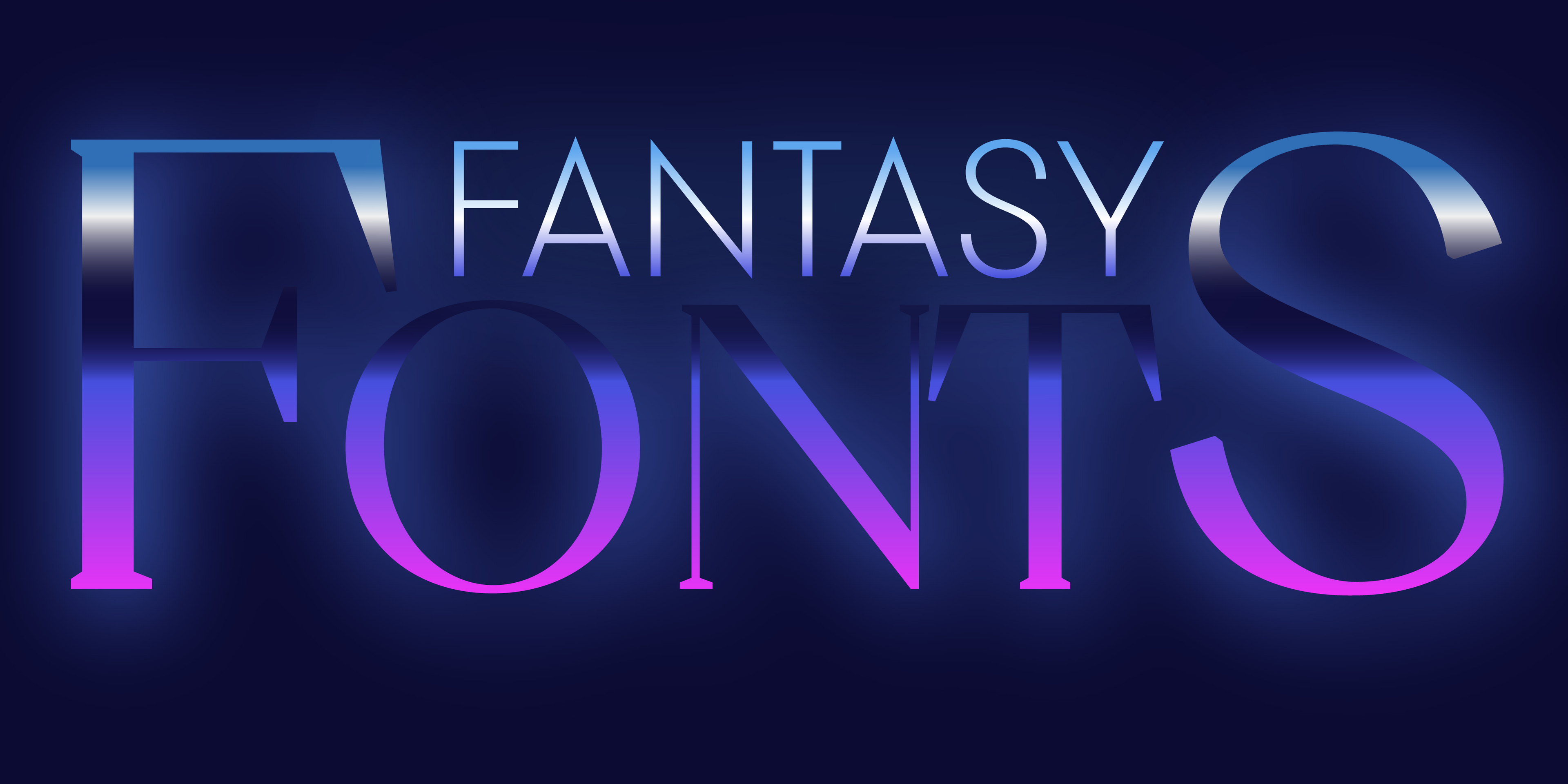
Fuentes de fantasía con un toque natural.
Veamos la primera fuente de fantasía. Se llama Kijs y viene en muchos grosores. Aquí, estamos viendo Kijs Thin . Este grosor de fuente en particular es muy ligero y, si se escribe en mayúsculas, le da a cualquier texto una sensación mágica y de fantasía. La razón es que solo algunas de las letras, por ejemplo, G, I y R, son curvas y están ligeramente inclinadas hacia la izquierda, lo que agrega un concepto más orgánico.
Como puede ver en el ejemplo anterior, gran parte del estilo de fantasía se refleja en la paleta de colores y los efectos de diseño gráfico. Un bosque oscuro, un verde natural combinado con una viñeta negra y texto en color dorado le dan a este diseño de fantasía un aspecto moderno y elegante.
En el siguiente ejemplo, observamos la misma tipografía, pero en un grosor de fuente negro. “Black” es el grosor de fuente más audaz de todos los posibles. La tipografía sigue siendo femenina y natural, pero con esta audacia intensa, se siente más orgánica. Una tipografía más audaz como esta combina muy bien con paletas de colores de fantasía de tonos púrpura y rojo.
Fuentes de fantasía nítidas y puntiagudas
La siguiente tipografía que vamos a analizar se llama Acme Light . A primera vista, parece una tipografía sans serif geométrica moderna, pero cuando la configuras con un grosor de fuente más fino y en mayúsculas, el texto se convierte en una expresión de fantasía. Por ejemplo, observa el número tres o la letra S: los trazos de la letra comienzan y terminan en un estilo cortado, similar al metal. Si agregas un subrayado, una línea superior y un degradado de color en tonos rojos, obtendrás una imagen de fantasía moderna.
Apex es una fuente puntiaguda , lo que significa que las letras con punta, como A, V, W y M, se extienden más allá de la línea de altura de la mayúscula de la línea base y forman una punta afilada. Este estilo de fuente es excelente para diseños de fantasía porque comunica espadas y ciencia ficción de manera natural.
Usa Roma Regular cuando busques una tipografía humanista de contraste medio . Es lujosa y elegante y, con un efecto de brillo dorado, se convertirá rápidamente en un texto elegante y fantástico.
Fuentes serif de fantasía
El siguiente ejemplo es la fuente Quil ExtraLight . Es una tipografía serif con serifas cortas y terminales modernas simplificadas de punta ancha. El texto en esta fuente se ve fuerte y nítido y funciona bien para títulos de portadas de libros más largos cuando se escribe en letras mayúsculas con un espaciado estrecho entre letras. Quil es similar a la fuente Final Fantasy y tiene un toque medieval.
Utilizando la misma fuente que en el ejemplo anterior, esta serifa moderna también se puede utilizar en un grosor de fuente negrita para agregar más fuerza y potencia al texto. De esta manera, algunas de las características de la fuente, por ejemplo, los extremos en forma de pico afilado, resaltan más.
Bauhaus Rose Black está disponible en varios grosores de fuente, desde Thin hasta Black. Las serifas alargadas y los diferentes grosores de los trazos de las letras hacen que esta sea una tipografía serif de alto contraste ideal para usar como logotipos de fantasía y textos de titulares para títulos de libros y películas.
Fuente de fantasía divertida para niños
Y, por último, veamos una fuente de fantasía para proyectos infantiles . Esta tipografía se llama Vole Bold; tiene un estilo general redondo, pero tiene unos contadores redondos únicos (los agujeros o formas internas de las letras). Esta característica le da al texto un efecto acuoso. Cuando combinas Vole con un color brillante como el violeta neón y un azul más oscuro y apagado, los diseños adquieren un aire de fantasía más alegre, adecuado para niños.